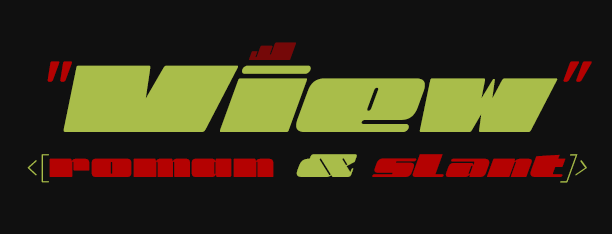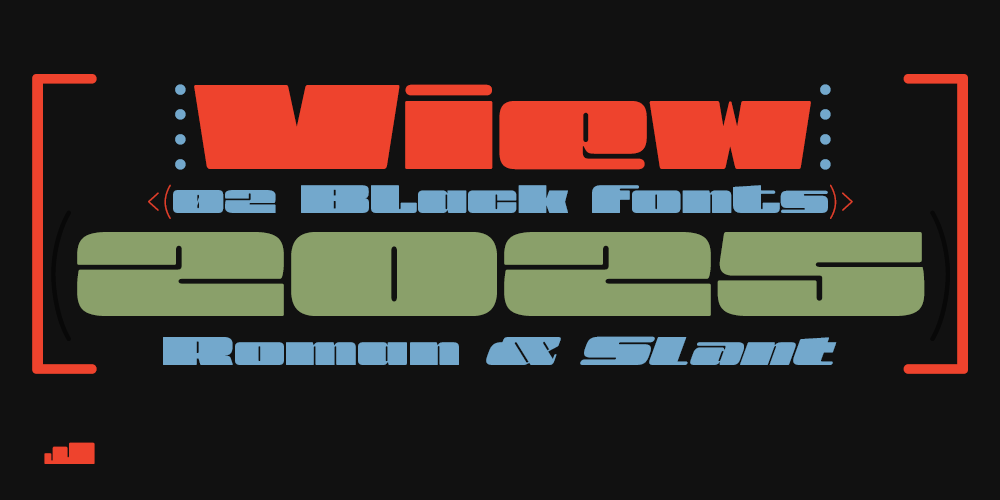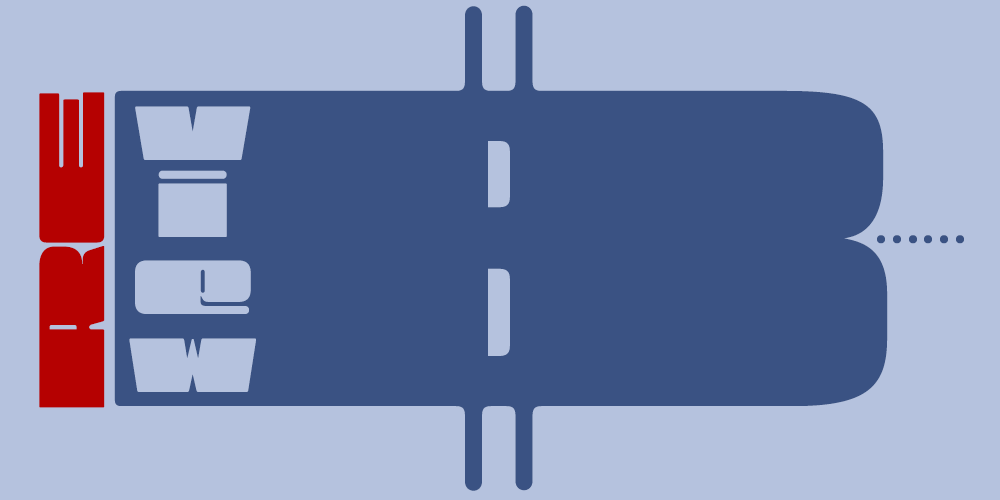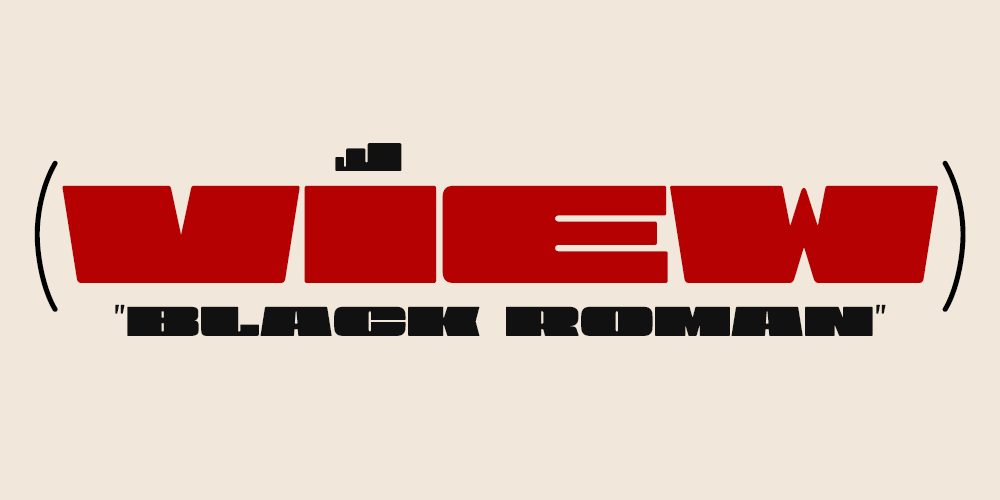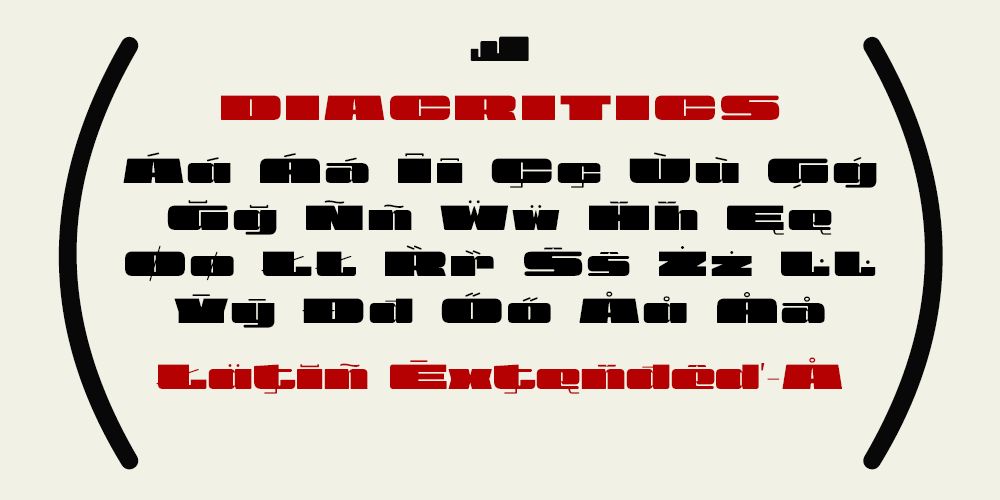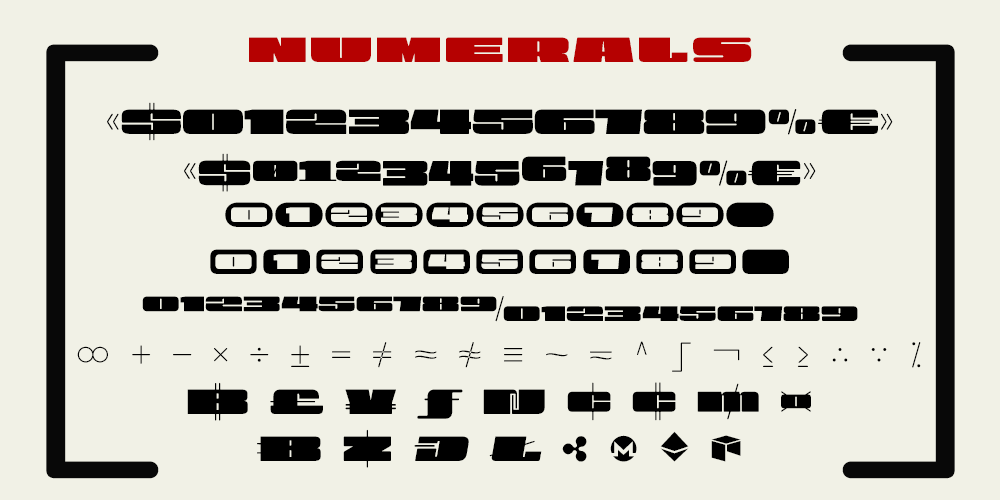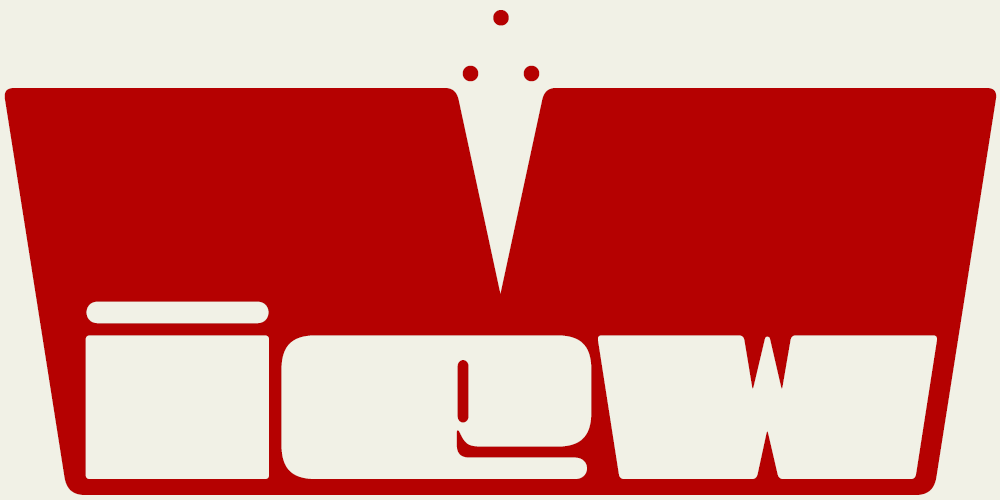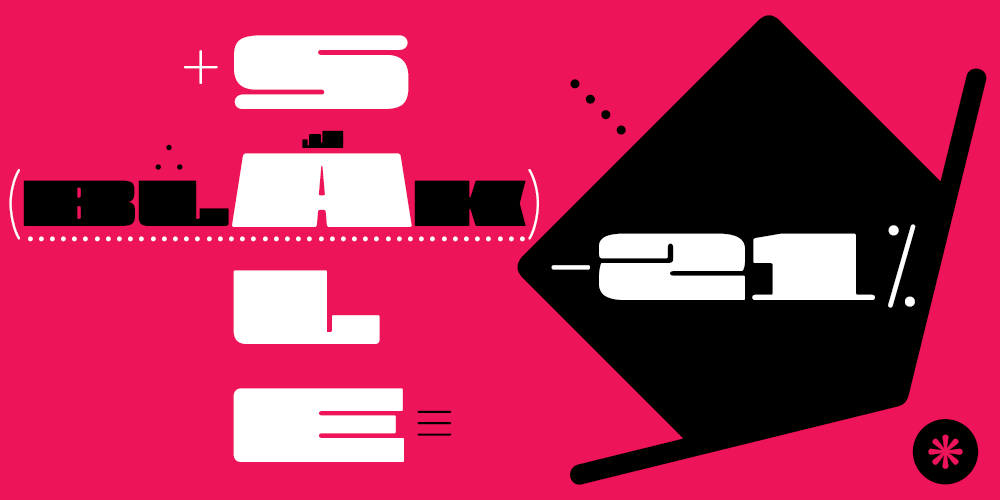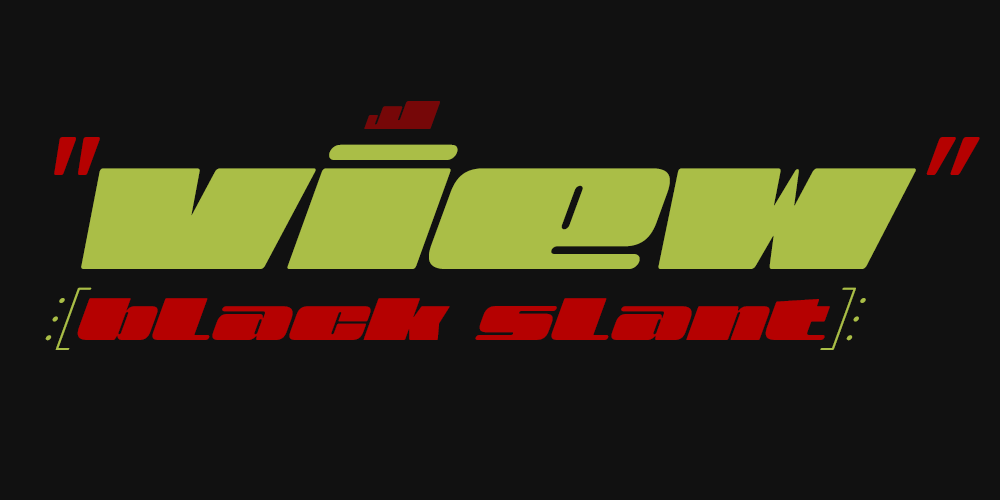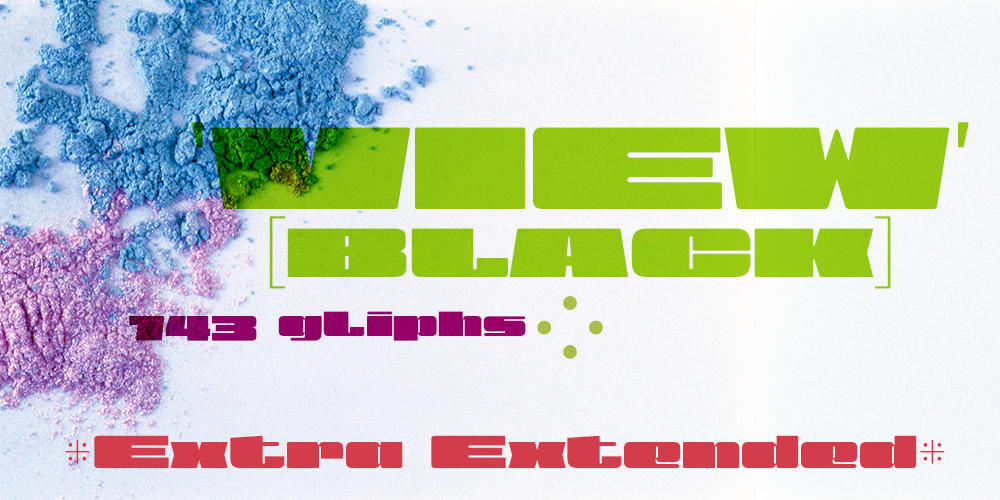
Sus formas son pura potencia, con un equilibrio perfecto entre la fuerza del estilo Roman y el dinamismo del Slanted.
re(View) Extra Expanded
Estilo: Black, Sans Serif, Display, Slanted, Thickset
Proporción: Extra expanded, Ultra wide, Slant, Oblique
Latin-Extended: Latín Básico, Europa Occidental, Central & Oriental.
Funciones OpenType: Additional languages, All Alternates, Capital Spacing, Contextual Alternates, Denominators, Discretionary Ligatures, Fractions, Historical Forms, Inferiors, Kerning, Localized Forms, Numerators, Oldstyle Figures, Ordinals, Scientific Inferiors, Slashed Zero, Standard Ligatures, Subscript, Superior letters, Superiors, Superscript.
w/ 166 alternates: Numbers & Letters
View, diseñada para destacar, impactar y dominar.
Su proporción exageradamente ancha y su peso Black se expresan sobremanera: cada letra es una declaración de presencia, una explosión de carácter que no pasa desapercibida. Está hecha para los que aprecian la contundencia de las tipografías súper gruesas y extra anchas.
Sus formas son pura potencia, con un equilibrio perfecto entre la fuerza del estilo Roman y el dinamismo del Slanted. Ideal para titulares que quieren hacerse oír, para marcas que desean destacar o para diseños que exigen carácter.
Diseñada en dos versiones
—Black y Black Slant— View es una fuente que combina la fuerza de un trazo poderoso con la elegancia de los detalles refinados.
La audaz proporción extra expandida es lo que hace a View verdaderamente única. He acortado intencionalmente los ascendentes y descendentes para amplificar la inmensidad de su anchura.
Cada letra de View irradia una presencia imponente, las formas son rotundas, casi monumentales, pero al mismo tiempo sofisticadas, tienen un acabado redondeado en todas sus esquinas y ángulos, lo que le confiere una personalidad distintiva, mantiene un contraste impactante entre la robustez de las astas y la delicadeza de sus contra formas, sorprendentemente finas y redondeadas.
Las curvas, los espacios, y el kerning los he ajustado minuciosamente para que mantengan una relación coherente y equilibrada, acostumbro a definir muchas de estas medidas con cifras de secuencias matemáticas áureas, para garantizar que View no solo llame la atención, sino que también se lea con fluidez y equilibrio, además, las innumerables correcciones ópticas aplicadas en ambas versiones (Roman & Slant) garantiza que tus textos no solo sean impactantes, sino también armoniosos y equilibrados.
El contraste deliberado crea una tensión visual fascinante con la corpulencia de las letras, además, he incluido algunos signos de puntuación adicionales, que puedes utilizarlos como elementos de diseño, abriéndote un mundo de posibilidades creativas.
Dinamismo con la versión Slant
La versión Slant, tiene una inclinación decidida de 20 grados, por esto le añade un impulso visual inmediato: dinamismo, velocidad, actualidad. View Slant no es simplemente una versión inclinada, es una reinterpretación del conjunto bajo una lógica de movimiento, con todas las correcciones ópticas necesarias para garantizar que el resultado sea tan armonioso como impactante. Ideal para proyectos que exigen movimiento y frescura, sin perder un ápice de legibilidad.
Tecnología y versatilidad
View Black está equipada con funciones *OpenType* de última generación: alternativos tipográficos, fracciones automáticas, signos matemáticos, flechas y mucho más, también soporta el conjunto de caracteres: Latin Extended-A, por lo que está lista para dialogar con una amplia diversidad lingüística.
View Black es la elección perfecta para proyectos que exigen visibilidad y personalidad, brillará allí donde el diseño exige presencia, impacto y legibilidad sin compromisos:
- Titulares monumentales:los subtítulos son para tímidos.
- Posters y cartelería: que griten incluso en silencio.
- Logotipos y branding: para marcas que no se esconden.
- Packaging y señalización: porque lo importante es que se vea.